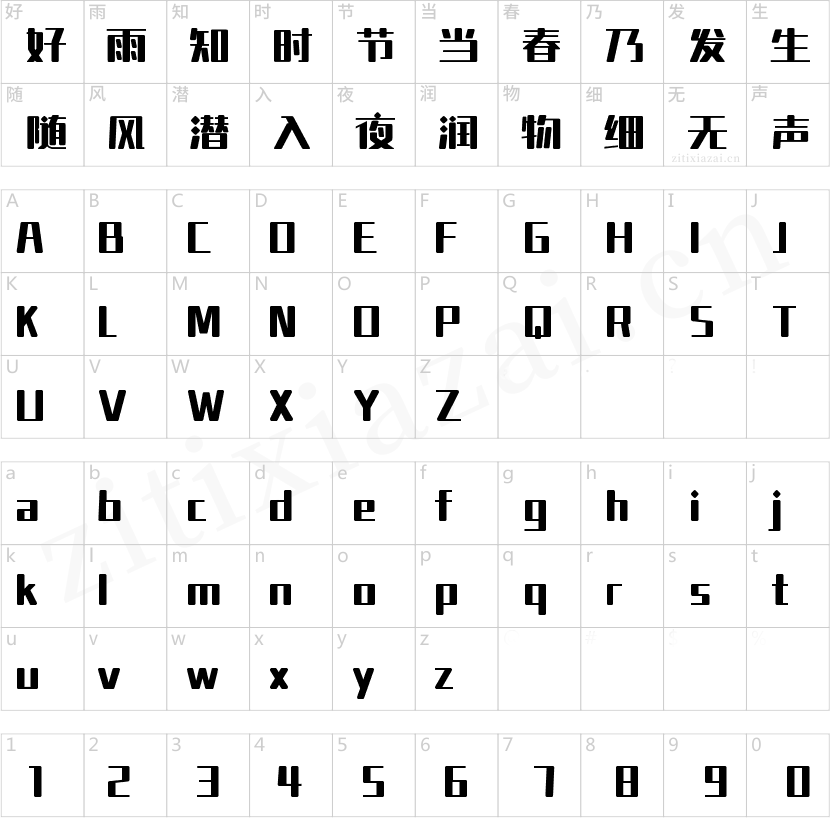
字魂闪烁凝光体
字魂闪烁凝光体,这款字体结构工整、笔画清晰,兼顾美观与易读性,适用于标题、正文、海报、包装、LOGO 等多种场景。字形优雅稳定,风格百搭耐看,适配日常排版与创意设计,让文字呈现更舒适、更具质感。字魂闪烁凝光体一笔一画,皆是细节,以均衡的比例、流畅的线条打造舒适视觉体验,字形端正大气,风格简约现代。无论是商业设计、品牌宣传还是日常排版,都能轻松驾驭,让文字更有格调与力量。字魂闪烁凝光体字体下载。
字魂字体字魂闪烁凝光体字体是由字魂创意字库设计并生产的一款可商用的字体,被收录于字魂先锋系列。该字体支持GB-2312标准,包含6942个中文、字母、符号和数字,字体类型偏向创意字体,具有活泼、可爱的风格,在市面上广泛用于母婴、化妆美容、标题字等场景。